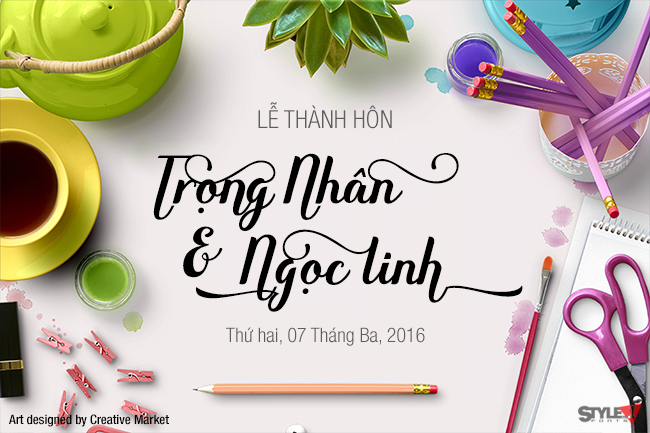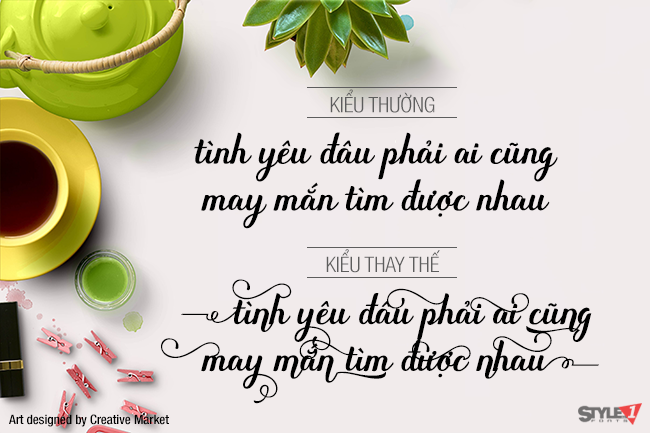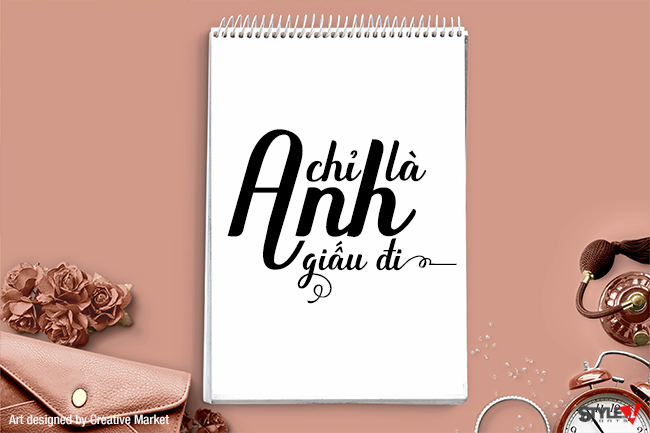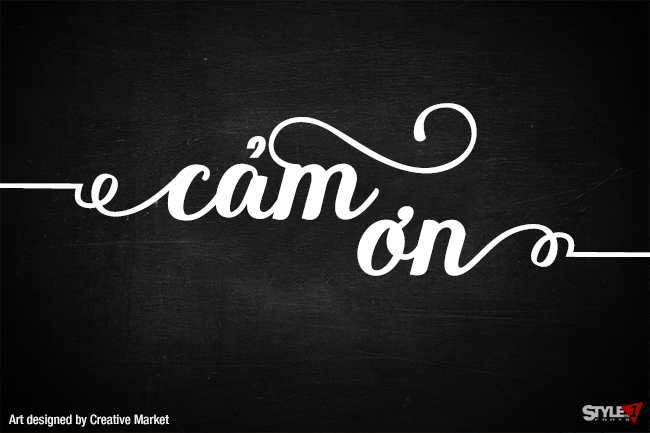
Angellife là một font Script đẹp mắt, phù hợp cho thiệp cưới, thiệp chúc mừng, áo thun, logo hoặc bất kỳ thiết kế nào bạn tạo ra. Font đi kèm đầy đủ bộ ký tự tiêu chuẩn, ký tự thay thế (Alternates), dấu câu, glyphs quốc tế và các Stylistic Alternates, giúp bạn linh hoạt sáng tạo trong nhiều dự án thiết kế khác nhau.